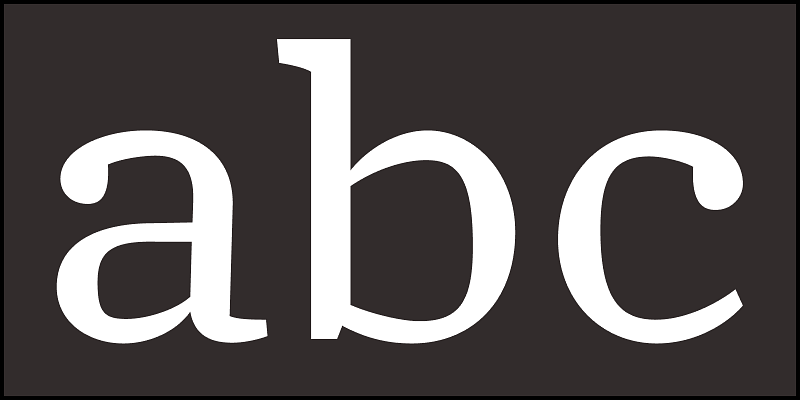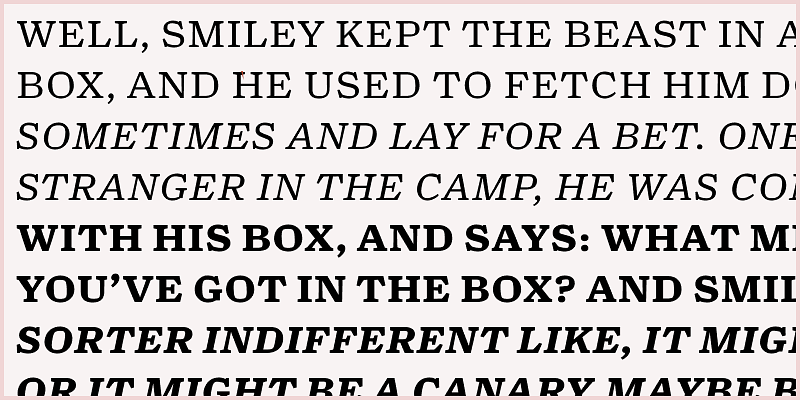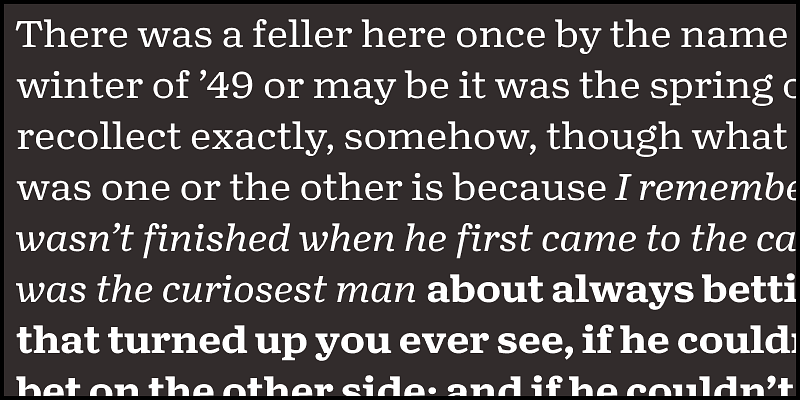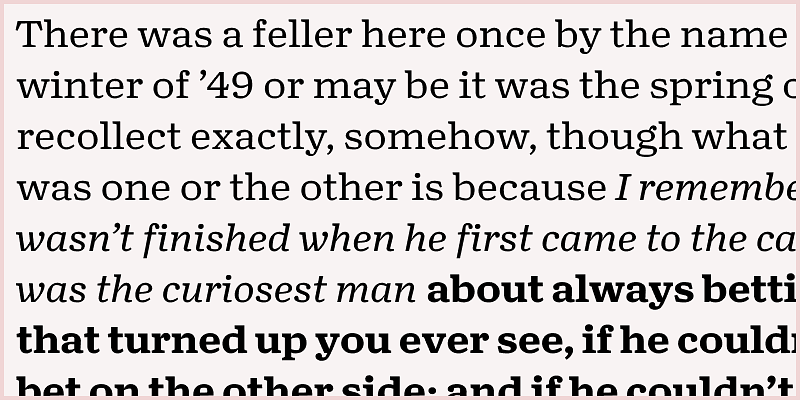
Tandis que les polices à empattement classiques sont synonymes d’urbanité et de bonnes manières, Turnip est plus grossière et prosaïque, le type de police tout à fait compatible avec un niveau de langue brut de décoffrage. David Jonathan Ross a su créer une tension énergique entre les formes internes et externes de Turnip pour lui conférer du dynamisme, alors que les traits prononcés et les empattements solides donnent lieu à des paragraphes denses mettant l’accent sur l’horizontale. Ce n’est pas la police du livre que lit votre grand-père, mais elle est tout aussi lisible.